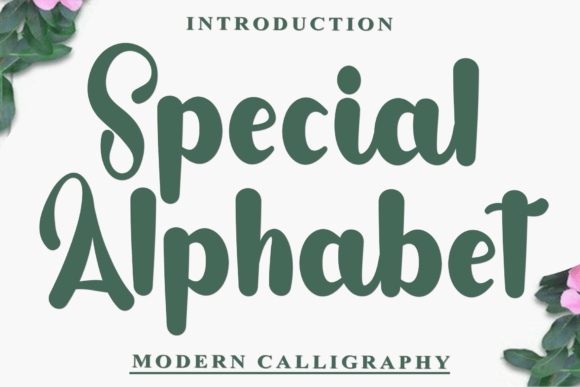
Special Alphabet
適切なデザイン要素を見つけるのは難しい場合がありますが、Special Alphabetは作品を即座に引き立てる優れたコレクションを提供します。
POD(オンデマンド印刷)製品、結婚式の招待状、またはソーシャルメディアのグラフィックを作成している場合でも、Special Alphabetは理想的です。